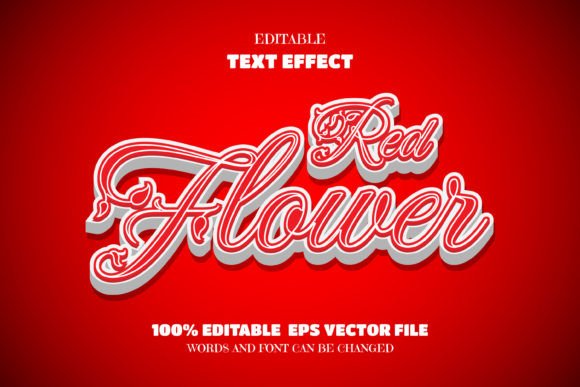
Red FlowerText, Editable Font Effect
Jika Anda mencari aset berkualitas tinggi seperti Red FlowerText, Editable Font Effect, paket premium ini adalah pilihan fantastis untuk proyek kreatif Anda.
Dibuat dengan presisi, Red FlowerText, Editable Font Effect menyediakan vektor yang bersih, tipografi yang halus, serta lisensi komersial untuk ketenangan pikiran Anda.
Baik Anda membuat produk POD (Print on Demand), undangan pernikahan, atau grafis media sosial, Red FlowerText, Editable Font Effect adalah pilihan yang sangat ideal.